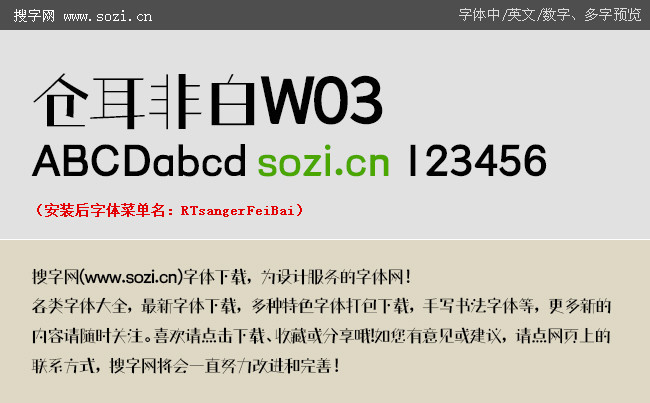
倉(cāng)耳非白W03
搜字網(wǎng)提供一款倉(cāng)耳非白W03中文藝術(shù)字體下載,倉(cāng)耳非白是一款粗細(xì)對(duì)比明顯、風(fēng)格強(qiáng)烈、擁有5個(gè)字重的家族字體,結(jié)構(gòu)方整,筆形簡(jiǎn)潔、利落,帶有明顯區(qū)別于其他字體的風(fēng)格。是倉(cāng)耳字庫(kù)推出的一款支持全領(lǐng)域永久免費(fèi)商用的個(gè)性藝術(shù)字體。
• 風(fēng)格類別: 現(xiàn)代藝術(shù)體